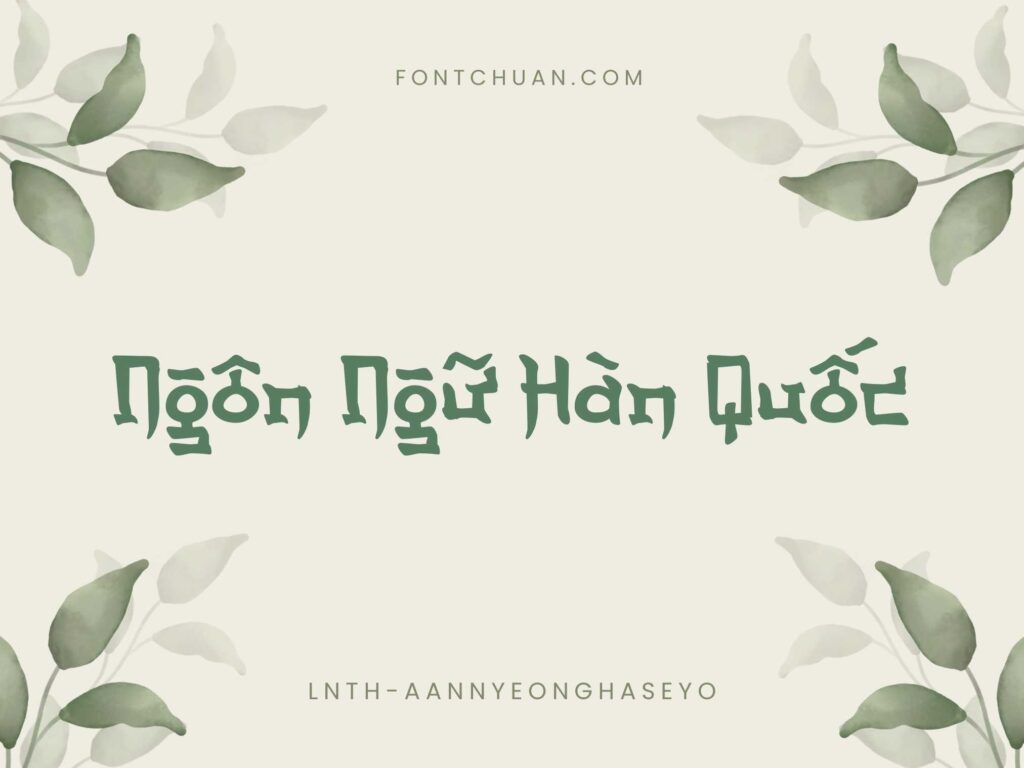
Font LNTH Aannyeonghaseyo Việt Hóa
A Annyeong Haseyo là một phông chữ được thiết kế bởi Wahyu Eka Prasetya, lấy cảm hứng từ phong cách chữ viết Hàn Quốc. Phông chữ này mang đậm nét Á Đông, với các đường nét mềm mại và uyển chuyển, tạo nên sự thân thiện và ấm áp cho các thiết kế. Với sự Việt hóa của LNTH, A Annyeong Haseyo hỗ trợ đầy đủ các ký tự tiếng Việt, giúp người dùng dễ dàng áp dụng trong các dự án đa ngôn ngữ. Phông chữ này được sưu tầm và đăng tải bởi thành viên của Font Chuẩn nhằm đáp ứng nhu cầu đa dạng của cộng đồng thiết kế.
Về đặc điểm thiết kế, A Annyeong Haseyo sở hữu các ký tự được thiết kế tỉ mỉ, mang lại cảm giác nhẹ nhàng và tự nhiên. Phông chữ này đặc biệt phù hợp cho các dự án như thiệp mời, bìa sách, poster, logo và các ấn phẩm quảng cáo, nơi cần sự tinh tế và ấn tượng mạnh mẽ. Ngoài ra, A Annyeong Haseyo cũng thích hợp cho các sự kiện như lễ hội, sinh nhật, Valentine và Trung thu, mang lại không khí lãng mạn và nghệ thuật. Trong lĩnh vực ngành nghề, phông chữ này được ứng dụng rộng rãi trong quảng cáo, thiết kế thiệp cưới, giáo dục và công nghệ, góp phần tạo nên sự độc đáo và thu hút cho các sản phẩm và thương hiệu.